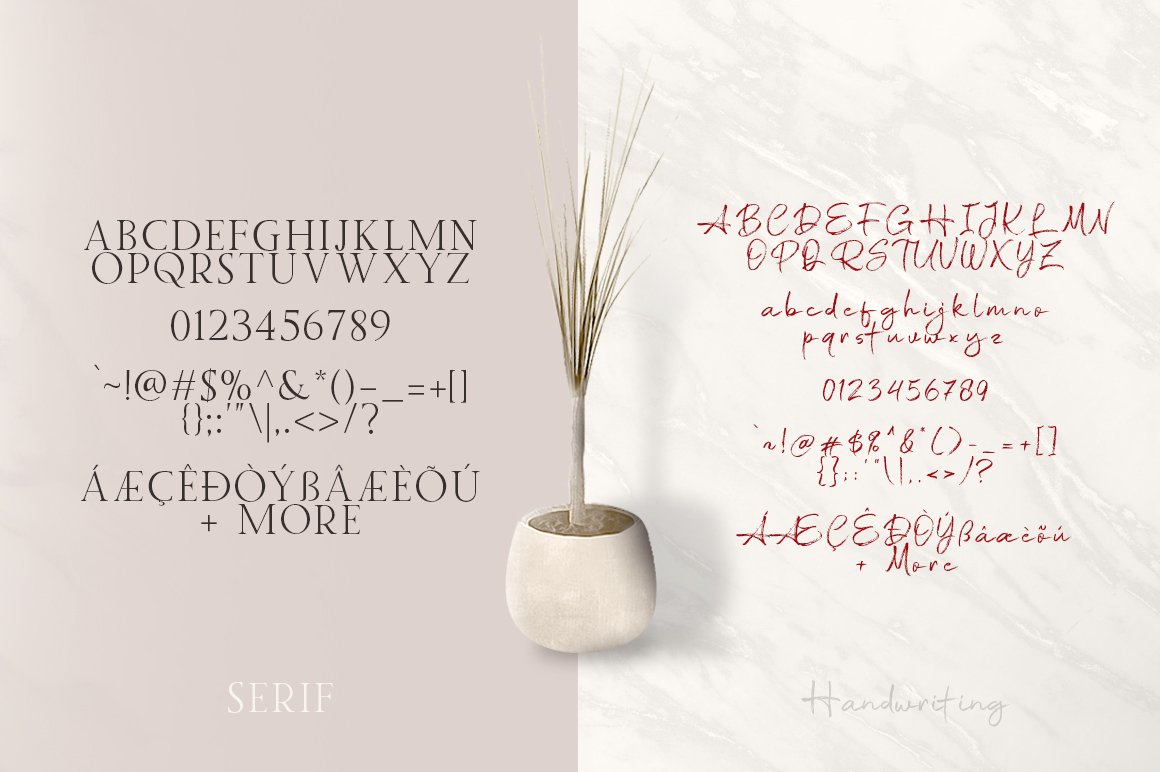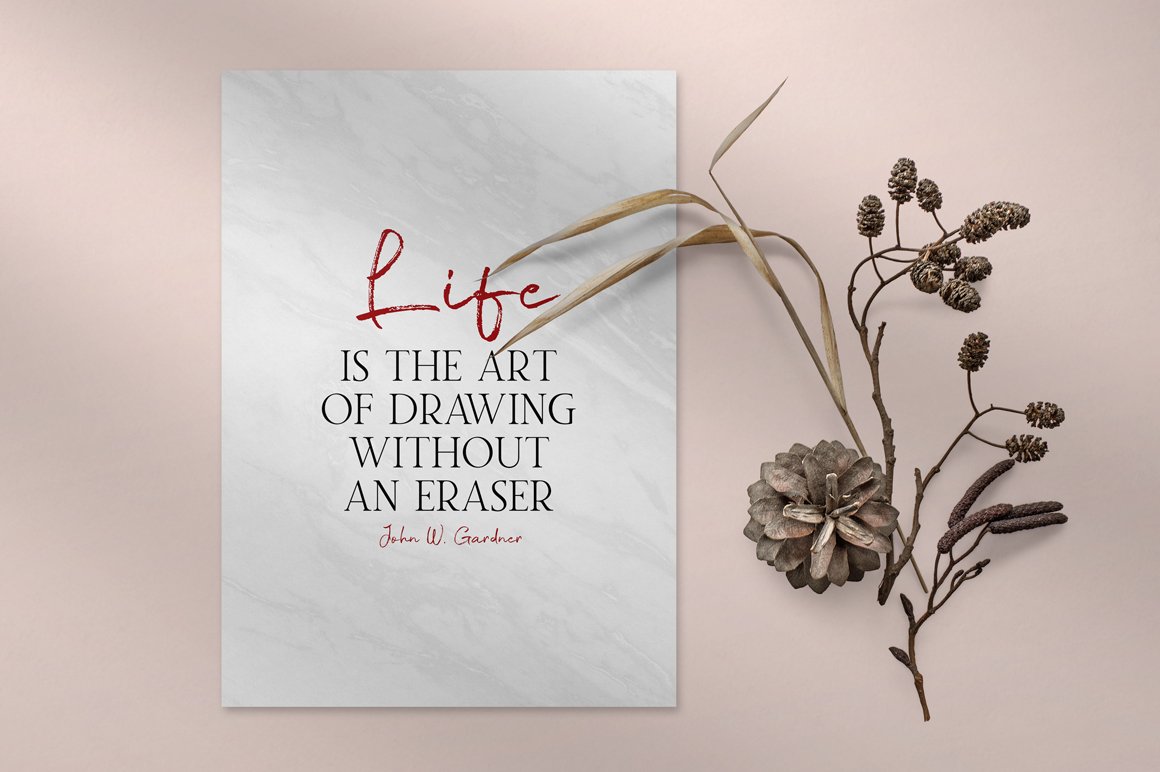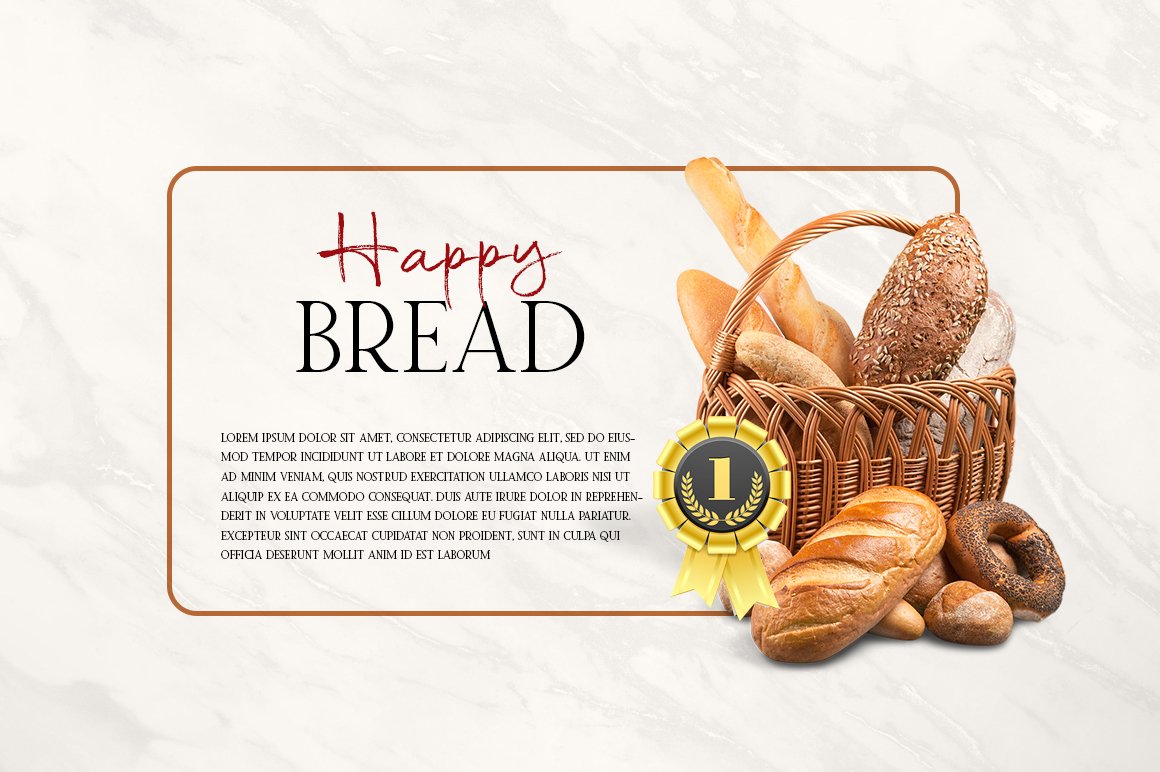
Twice Writing Font
Description de Twice Writing Font
La police Twice Writing Font est une police de script moderne et amusante, au style frais et moderne avec la police Serif. Vous pouvez combiner script et Serif pour obtenir des résultats étonnants. Police d’écriture deux fois adaptée au logo, à la marque, à la carte de vœux, à l’affiche et à tout design que vous créez.